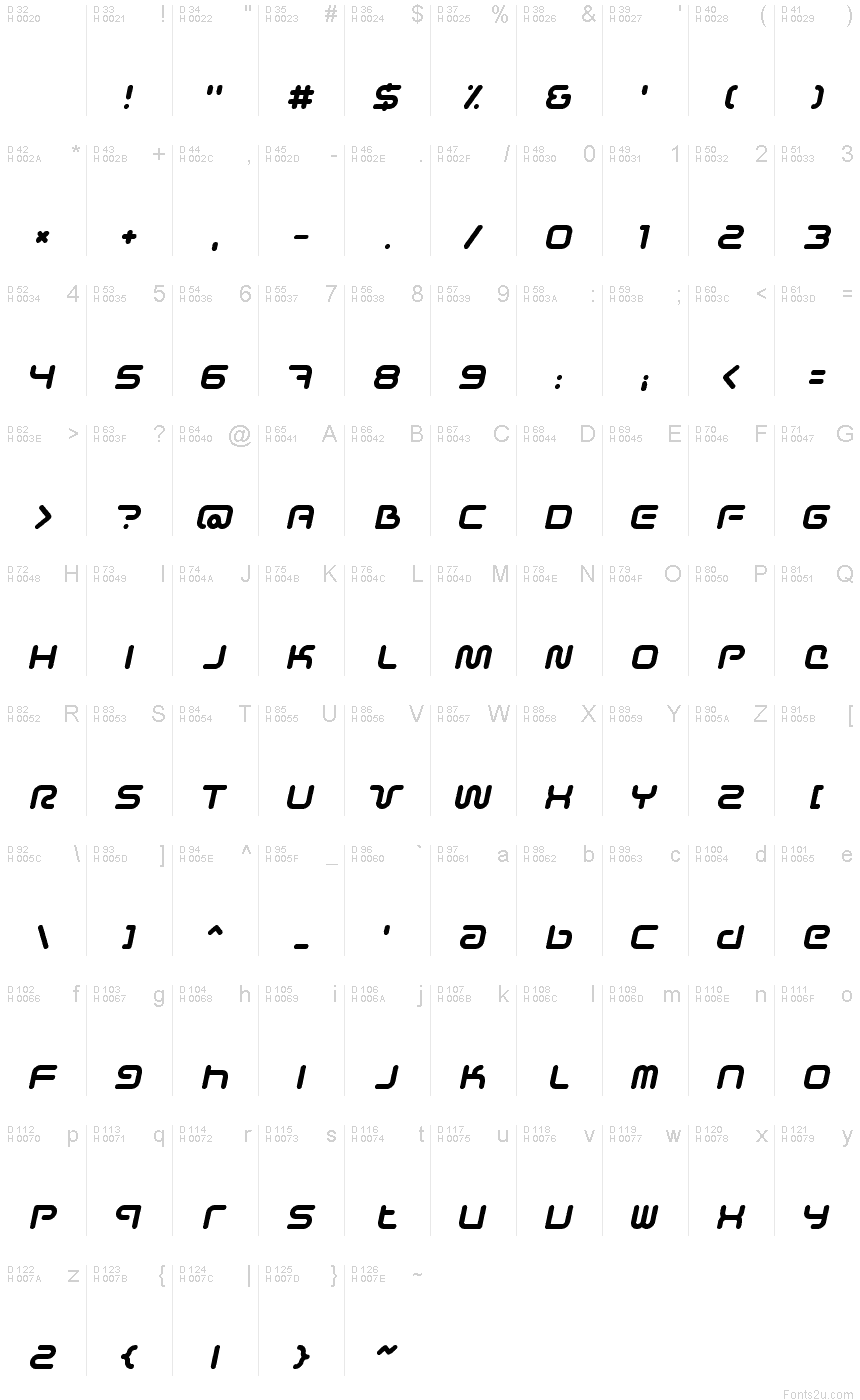
Sci Fied, firmata dustBUST Fonts, è un carattere display corsivo, gratuito e futuristico, che richiama l'estetica elegante del branding sci-fi di fine anni '90. Le maiuscole si protendono in avanti con tratti ampi e arrotondati, aperture nette e lunghi segmenti orizzontali che rendono l'alfabeto veloce, sintetico e leggermente aerodinamico.
Si adatta perfettamente a loghi di videogiochi, titoli di poster, grafiche per eventi tecnologici, copertine di album e cartelli dove serve un font gratuito con una forte voce elettronica. Dato che le lettere sono larghe, fluide e già inclinate, è ideale anche per titoli brevi, branding ispirato alle interfacce e monogrammi che cercano un aspetto tecnologico aerodinamico.